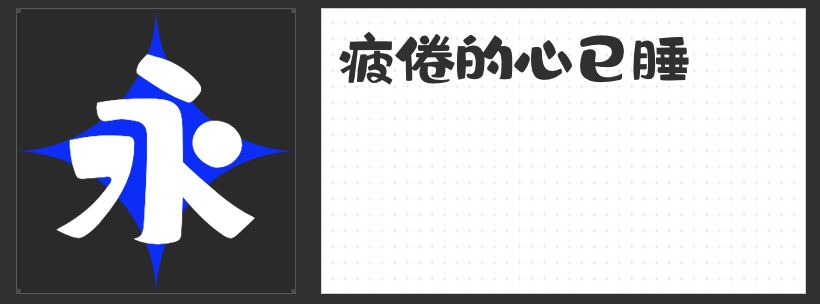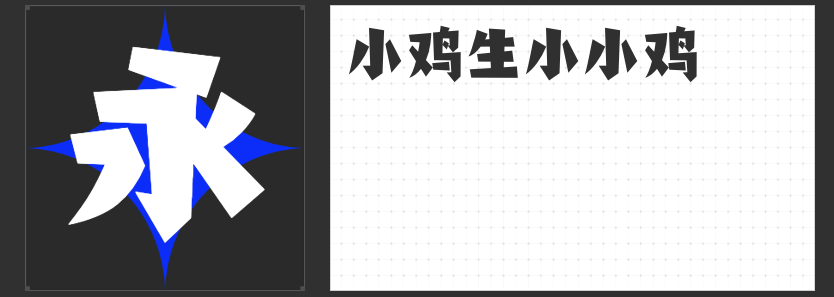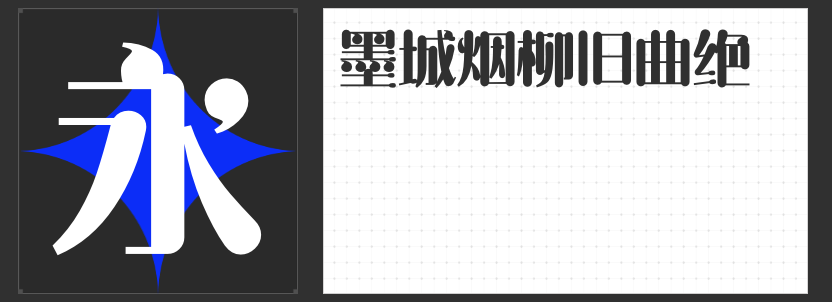
四款创意字体推荐:解锁LOGO设计的艺术张力
在品牌视觉传达中,字体不仅是信息载体,更是情感与个性的具象化表达。以下四款兼具艺术性与辨识度的创意字体,通过独特的结构设计与文化内涵,为LOGO设计注入鲜活生命力。
一、励字明姿简
这款字体以几何图形为灵感,将传统汉字结构解构重组。竖画粗壮如魔法权杖,横画纤细似灵动轨迹,形成强烈的视觉对比。圆润的笔画转折与留白空间,既保留了汉字的书写韵律,又赋予其未来科技感。其设计突破常规字重比例,通过竖粗横细的对比强化视觉焦点,尤其适合科技、教育、文化类品牌的LOGO设计,传递专业与创新的双重气质。
二、励字俊林简
以“竹”为设计母题,这款字体将自然意象融入笔画形态。圆弧转角如竹节般温润,留白处理似竹叶间隙,整体呈现出“疏影横斜”的诗意美感。其笔触虽无尖锐棱角,却通过粗细变化的节奏感,构建出灵动的视觉韵律。这种“柔中带刚”的设计哲学,使其成为文化创意、生活美学、健康养生类品牌的理想选择,既能传递东方文化的含蓄之美,又不失现代设计的简洁力量。
三、小豆岛默陌写意水墨简
这款字体将传统书法与现代手写风格完美融合。笔尾的锋芒与拐转的浑圆形成张力,拉长的笔锋如行云流水,浑圆的墨点似溅落宣纸的墨韵。其设计突破书法字体的固有框架,通过线条的粗细变化与灰度层次,营造出“似与不似之间”的艺术意境。适用于艺术展览、文创产品、茶饮品牌等场景,既能彰显文化底蕴,又能以灵动的笔触吸引年轻消费群体。
四、励字憨憨简
以圆弧形笔画为核心,这款字体构建出呆萌可爱的视觉语言。饱满的字形如充气玩具般富有弹性,装饰性的圆点与曲线增添活泼气质。其设计通过夸张的笔画比例与简化结构,强化了字体的识别度与记忆点。这种“去严肃化”的设计策略,使其成为儿童教育、亲子娱乐、宠物品牌等领域的首选,能快速拉近与受众的情感距离。
这四款字体通过不同的设计语言,展现了汉字在LOGO设计中的无限可能。从几何抽象到自然意象,从水墨意境到童趣表达,它们以独特的视觉符号系统,为品牌构建起差异化的视觉身份,让每一个LOGO都成为讲述品牌故事的视觉载体。